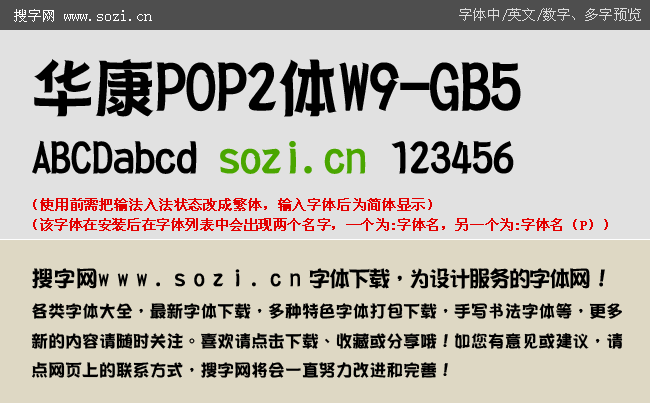
華康POP2體W9-GB5
搜字網(wǎng)提供一款華康POP2體字體下載,華康POP2體是一種手寫所呈現(xiàn)出來的美術(shù)化字體,字體特色在筆劃落筆與收筆處,帶有彎勾上揚,給人嫵媚圓潤的細致感,在傳統(tǒng)的POP字體當中,尋求一種剛?cè)峤Y(jié)合的古典美意境。適用于商場促銷、產(chǎn)品賣場、餐廳美食海報等廣告宣傳使用。